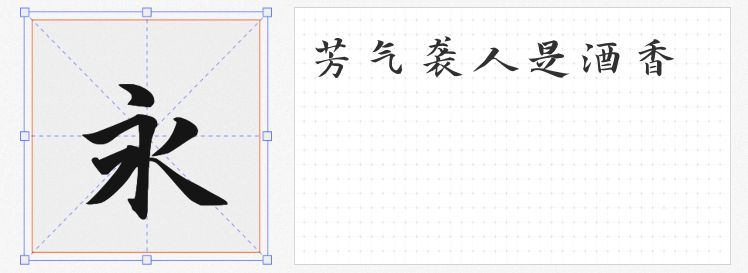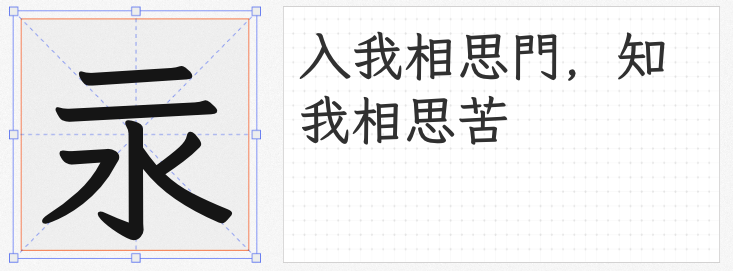
新中式设计的核心在于“以今承古”,而手写字体的运用恰是连接传统文脉与现代审美的桥梁。以下四款字体以经典楷书为根基,通过现代设计思维重构字形,既保留手写温度,又赋予其适配当代视觉语境的独特气质,为品牌、包装、空间等设计领域提供更具文化深度的文字解决方案。
1. 寒蝉书体·春秋 春风
基于开源字体「演示春风楷」拓展设计,寒蝉书体·春秋 春风延续了手写楷书的自然笔意,笔画粗细过渡如行云流水,起收笔处微提的笔锋暗含书写节奏。字形结构疏朗,中宫适度收紧,布白均匀中透出呼吸感,整体气质清雅而不失力度。其简约而不失韵味的设计,适合茶文化、文房器物等领域的视觉设计,能以文字本身传递“静中有动”的东方哲学。
2. 月星楷 繁 Bold
以「月星楷」为原型修改的繁体版本,通过OpenType技术实现「简入繁出」的智能匹配,解决一简多繁的排版难题。Bold字重强化了笔画的骨力,横细竖粗的对比增强视觉张力,折笔处棱角分明却因笔画的自然过渡而避免生硬。繁体字形自带的历史感与现代字重的结合,使其在古籍出版、传统工艺展示等场景中,既能传递文化厚重感,又符合当代阅读习惯。
3. 寒蝉龙藏楷书 Regular
基于开源字体「有字库龙藏体」拓展设计,寒蝉龙藏楷书融合了北碑的刚劲与唐楷的法度,笔画粗壮有力,起笔如刀刻,收笔含蓄内敛。字形结构严谨,重心平稳,通过适度压缩中宫提升字间距,避免密集排版时的视觉压迫感。这款字体适合文化类品牌主视觉或历史题材展览设计,其端庄大气的风格能强化内容的权威性,同时保持手写楷书的鲜活感。
4. 玄冬楷书
以《马善政毛笔楷书》为基底,玄冬楷书修复原版字形误差并新增竖排排版特性,还原传统书法的章法之美。笔画粗细变化自然,飞白处理增添手写温度,竖向排列时字与字之间的呼应关系更显和谐。其独特的竖排优化设计,使其在古籍装帧、东方美学空间导视等场景中,能以文字布局传递“以竖为序”的传统审美,营造沉浸式文化体验。
这四款字体通过解构与重构传统书写范式,在保持手写温度的同时注入当代设计基因,为新中式创作提供更丰富的视觉表达维度。